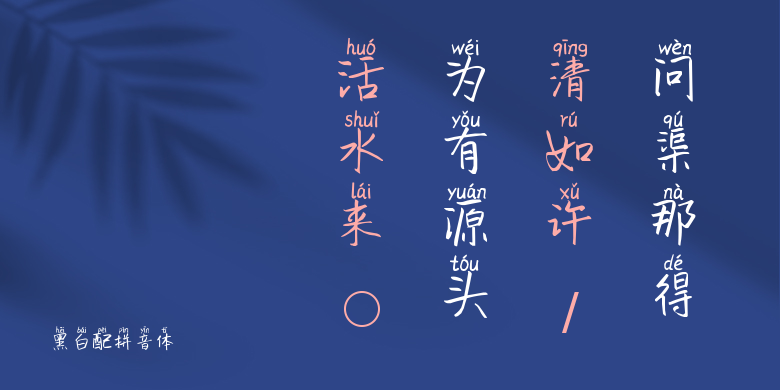
黑白配拼音体
黑白配拼音体,这款字体结构工整、笔画清晰,兼顾美观与易读性,适用于标题、正文、海报、包装、LOGO 等多种场景。字形优雅稳定,风格百搭耐看,适配日常排版与创意设计,让文字呈现更舒适、更具质感。黑白配拼音体一笔一画,皆是细节,以均衡的比例、流畅的线条打造舒适视觉体验,字形端正大气,风格简约现代。无论是商业设计、品牌宣传还是日常排版,都能轻松驾驭,让文字更有格调与力量。黑白配拼音体字体下载。